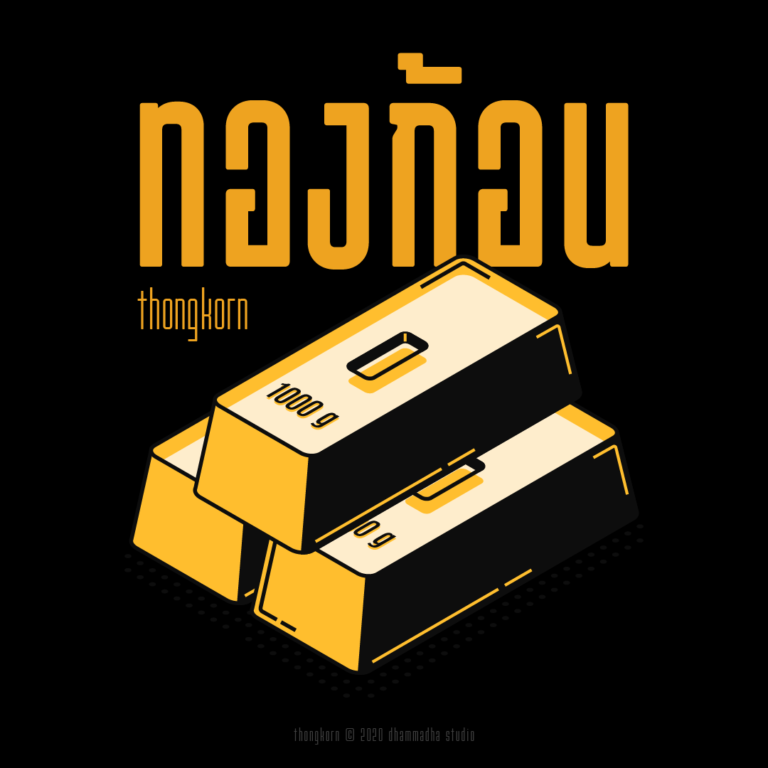
อีฟดรอวอิ้ง | Yves_yvesdrawing
ลายมือสุดน่ารักจากเพจ Yves_yvesdrawingบอกเลยว่า..กว่าจะตามตื๊อมาทำเป็นฟอนต์ได้นี่ยาวนานข้ามปีมาก ๆ
ชุดฟอนต์พาดหัว หนักแน่น มั่นคงตามแบบฉบับของ ธรรมดาสตูดิโอ
ฟอนต์พาดหัว บุคลิกเป็นกันเองเท่ด้วย เก๋าด้วย ใช้แล้วแฮปปี้
ฟอนต์ทรงสูง ครอบคลุมตั้งแต่ผอมบาง – อ้วนตันประหยัดพื้นที่การใช้งาน ทำให้สื่อสารได้มากขึ้น
ฟอนต์อ้วนตัน ย้อนยุคนิดๆ ร่วมสมัยหน่อยๆตามสไตล์ของ ธรรมดาสตูดิโอดิสเพลย์ พาดหัว เก๋ามาก!!!
เข้ามาเสริมทัพชุดฟอนต์ลายมือที่เคยเปิดให้ใช้งานมาก่อนหน้านี้ ที่มาที่ไปของแบบใกล้เคียงกัน แต่ปรับเปลี่ยนรูปลักษณ์การนำเสนอให้แตกต่างออกไปจากเดิม
ฟอนต์ “หนมปัง | nompang” เป็นฟอนต์แรกของเรา ที่เปลี่ยนมาใช้การจัดการตำแหน่งสระบน-ล่าง และวรรณยุต์ด้วยการใช้ anchor mark
เป็นชุดอักษรที่ได้รับแรงบันดาลใจและต้นแบบมาจาก logotype ของธนาคารกรุงเทพครับ แล้วใส่ความชอบของตัวเองลงไปนิด ทำให้ใช้งานได้ง่ายขึ้นอีกหน่อย ทันสมัยขึ้นมาอีกจึ๋งหนึ่ง (จึ๋งเดียวจริงๆ)
เป็นชุดอักษรที่ดึงบุคลิกมาจากรูปร่างของต้นกระบองเพชร ซึ่งมีลักษณะคล้ายกับการลากเส้นต่อจุด แม้ว่าเมื่อนำมาพัฒนาเป็นชุดอักษรแล้วได้มีการลดทอนบุคลิกที่ว่าลงไป แต่ก็ขอตั้งชื่อไว้ว่า “บองเพชร” พอให้ได้รู้ที่มาที่ไปครับ
หลังจากเคยทำชุดอักษรลายมือแบบประดิดประดอยไปแล้ว (ชุดอักษร : หวาน) คราวนี้ได้โอกาสจึงกลับมาทำลายมือแบบที่ดูธรรมชาติมากขึ้น คือ ลายมือที่ดูหยาบขึ้นนั่นเอง
ชุดอักษร “มณี-เมขลา” ชุดนี้ร่างลงกระดาษไว้นานประมาณหนึ่ง สักประมาณ 3-4 ปี เห็นจะได้ ที่เริ่มต้นอย่างนี้ ไม่ใช่อะไรหรอกฮะ คือจะบอกว่า ค้นที่มาที่ไปของชุดอักษรนี้ไม่เจอ T_T
“ชวนชิม” เป็นชุดอักษรใหม่ของเรา… แต่หน้าตาเก่า (มากกกก) สมัยเด็กๆ ที่บ้านเป็นร้านอาหารครับ ป้ายแรกที่จำได้ในชีวิตก็ป้าย “เชลล์ชวนชิม” เลยขอย้อนรอยวัยเด็กสักหน่อย
hook เป็นแบบร่างอักษร เมื่อครั้งผลิตงาน concept โดยนำอักษรไทยมาจัดวางสร้างสื่อภาพ และด้วยความบังเอิญ ฮูก ในการเขียนทับศัพท์ จะได้ความหมายที่แตกต่างออกไป ทำให้เกิดงานขึ้นมาอีกชิ้นหนึ่งความเป็นไปได้ที่เกิดขึ้น ทำให้เกิดแบบร่างชุดอักษรชุดนี้ขึ้นมา
samsen เป็นชุดอักษรที่ได้แรงบันดาลใจจากป้ายสถานีรถไฟสามเสน ตอนที่ขีดๆ เขียนๆ ลงในสมุดจด เป็นวันที่เดินทางกลับจากงาน TFACE#2 ถือว่าเป็นงานอักษรแรกๆ ที่ลองทำเลย แต่ไปๆ มาๆ ก็ยังไม่ได้เอามาทำให้เสร็จสมบูรณ์สักที
ฟอนต์ชุดนี้ เป็นฟอนต์ชุดแรกที่เริ่มทำขึ้นพร้อมๆ กับฟอนต์ “ป้ายไม้” มีการปรับรูปแบบหลายครั้ง จนเริ่มเข้าที่เข้าทาง เลยมีการเปลี่ยนชื่อเดิม เป็น “หิน” ที่มีทั้งเหลี่ยม ทั้งมน
ฟอนต์ชุดนี้ขึ้นแบบจาก whiteboard marker ตั้งใจทำออกมาให้ดูเป็นมิตรมากขึ้น และดูน่ารักขึ้นกว่าตัวก่อนๆ